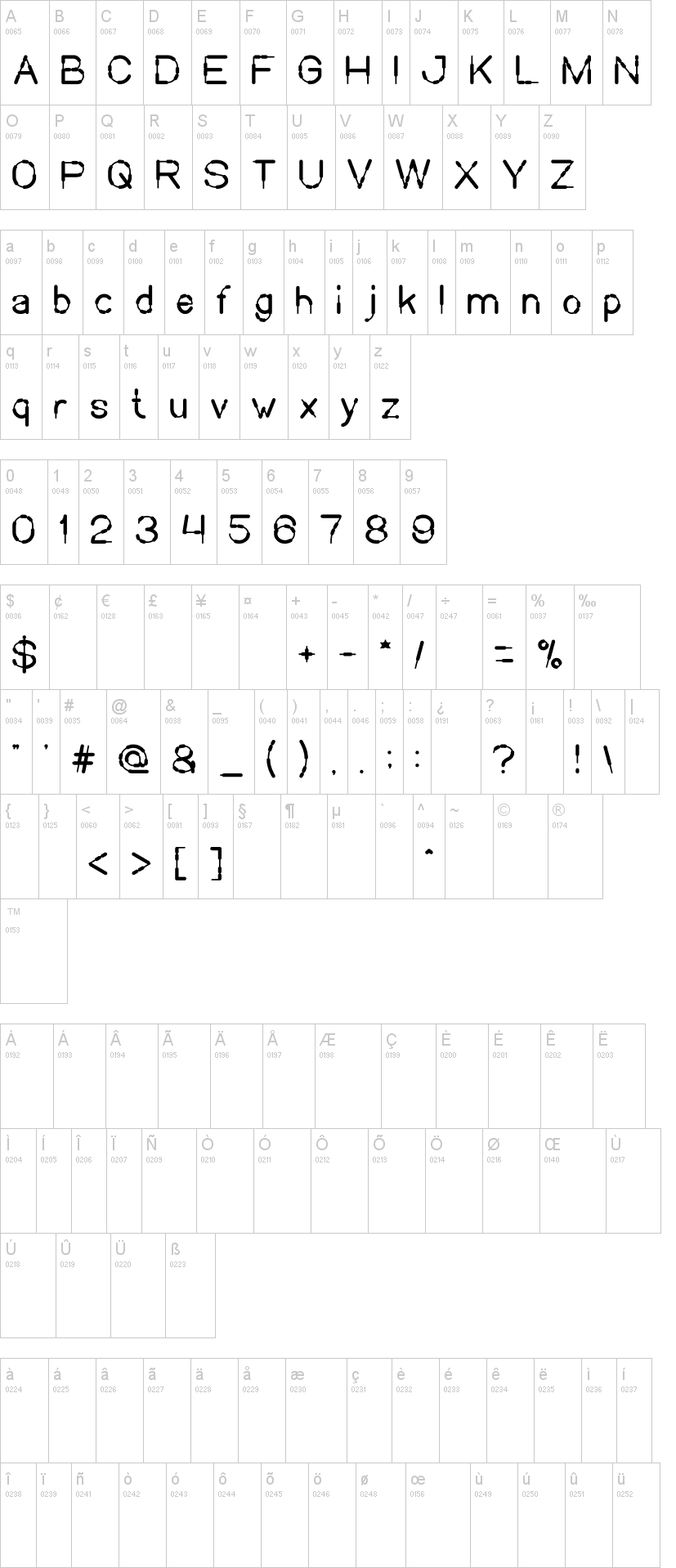
Sausage
Sausage 字体是一种手写风格的字体,以其独特的形态和细节而著名。它由一组大胆而流畅的线条组成,与传统印刷体不同,其字母和数字看起来更像是手写或绘制的。 Sausage 字体通常被用于印刷设计、广告和标志,因为它可以为这些设计添加独特的个性和风格。它也经常用于招贴、海报和网页设计中,以吸引人们的注意力并突出重点。 Sausage 字体有许多变体和风格,包括加粗、斜体和阴影版本,可以根据不同的设计需求进行选择和使用。
Sausage是一款非常不错的手写艺术字体,具有很好的视觉感,适合于文化类的宣传设计、商业类品牌的广告和产品包装设计以及个性化文字排版等较多场景。